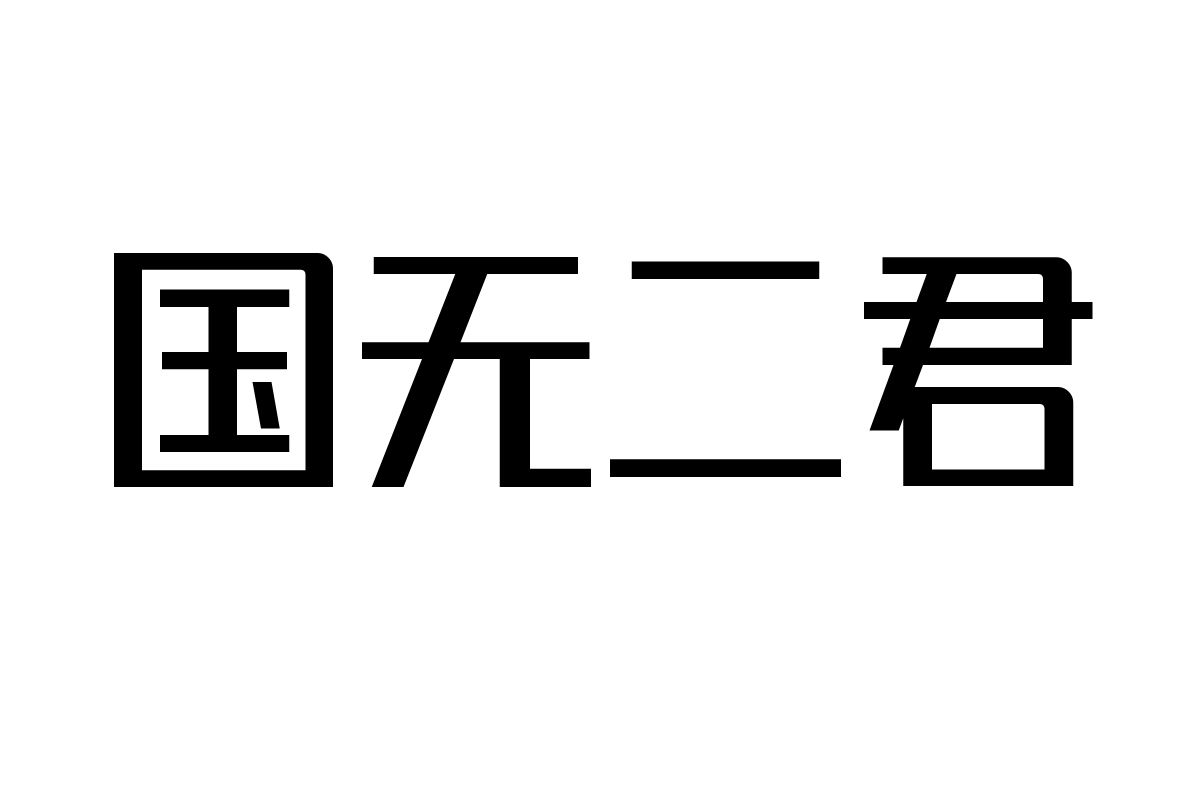
锐字潮牌真言是一款具有现代感和时尚气息的中文字体。这款字体的设计灵感来源于现代都市的潮流文化,线条流畅、简洁有力,给人一种强烈的视觉冲击力。
锐字潮牌真言采用了简约而不失个性的设计风格,字形结构紧凑,笔画粗细适中,既保留了传统汉字的韵味,又融入了现代设计的元素。它的笔画线条流畅自然,既有书法的韵味,又具有现代设计的美感。
锐字潮牌真言适用于各种商业广告、海报、包装设计等场合,能够很好地传达出品牌的个性和风格。同时,由于其独特的设计特点,也适合用于网络媒体、社交媒体等领域,成为年轻人喜爱的字体之一。